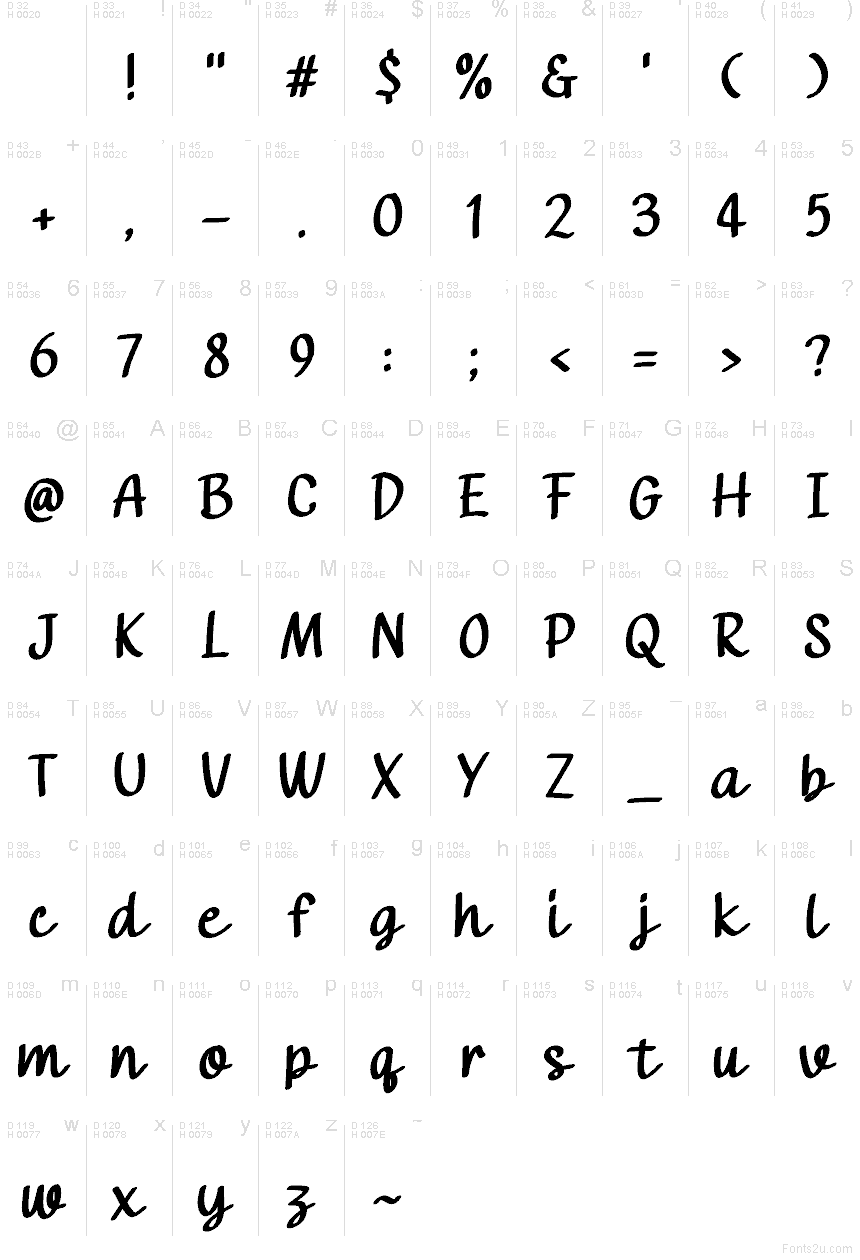
Шрифт Grender Jumps від Hello Good Studio - це безкоштовний рукописний шрифт із вільними штрихами пензля, заокругленими кінцями та злегка нахиленим ритмом, який здається швидше намальованим, ніж надрукованим. Літери зберігають невимушений, нерівний потік, а вузькі криві та кілька гостріших зрізів надають дизайну живого рукописного характеру.
Grender Jumps чудово підходить для плакатів, графіки для соціальних мереж, концепцій логотипів, оформлення цитат та пакування, де корисний стиль швидкої рукописної замітки. Цей безкоштовний шрифт привносить неформальний відтінок у меню кафе, етикетки, запрошення та заголовки, не виглядаючи при цьому надто вилизаним.